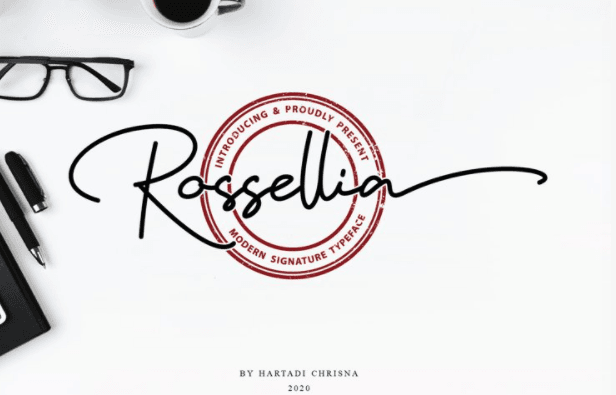
Rossellia - Modern Signature Typeface
Представляем и с гордостью представляем, Rossellia - это современный фирменный шрифт, этот шрифт идеально подходит для ваших проектов, таких как бренды, цитаты, приглашения, открытки, упаковка продуктов, заголовки, логотипы, письма, плакаты, дизайн одежды и т. Д.
1. Стандартные глифы и курсив
3. Есть много функций: альтернативы, лигатуры и автоматы перекоса.
7. Многоязычная поддержка